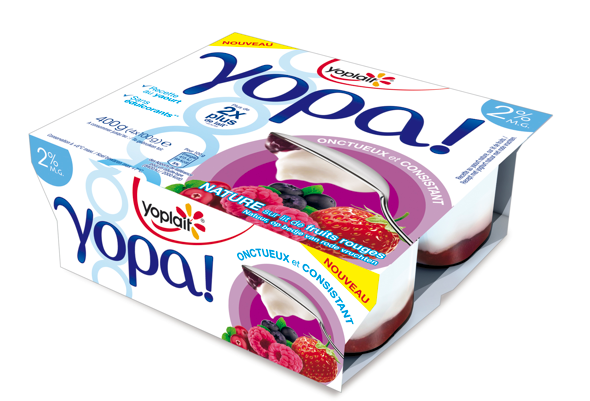
Je me sens yopaphobe tout d'un coup...
Bonsoir à tous.Yoplait a mis récemment sur le marché un nouveau produit dont le nom est écrit en caractères grecs, ce qui fait qu'il le vend sous le nom « yopa » en France et « gora » en Grèce (du moins peut-on le penser). Du jamais vu (?).Voyez l'image ci-dessous.J. M.